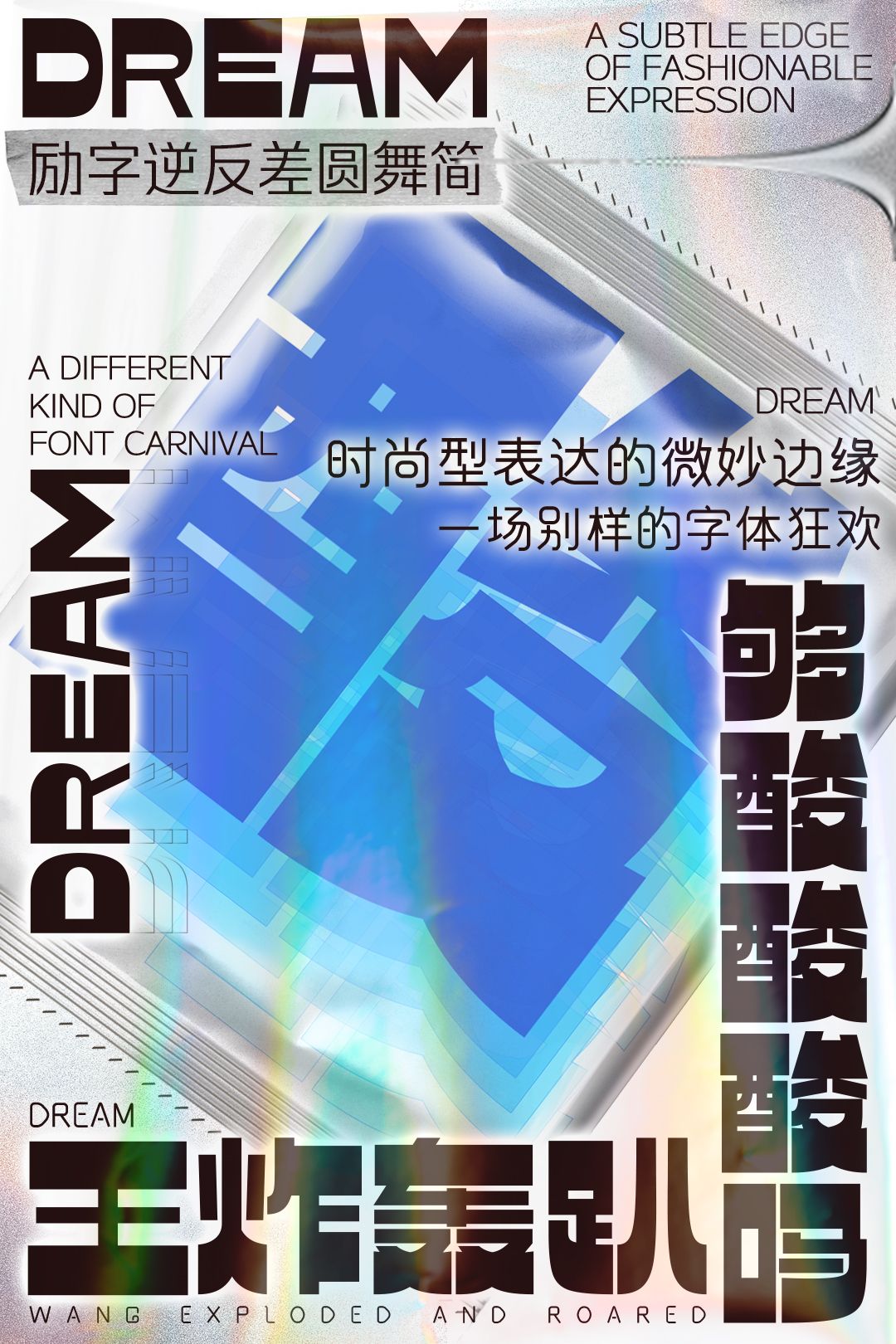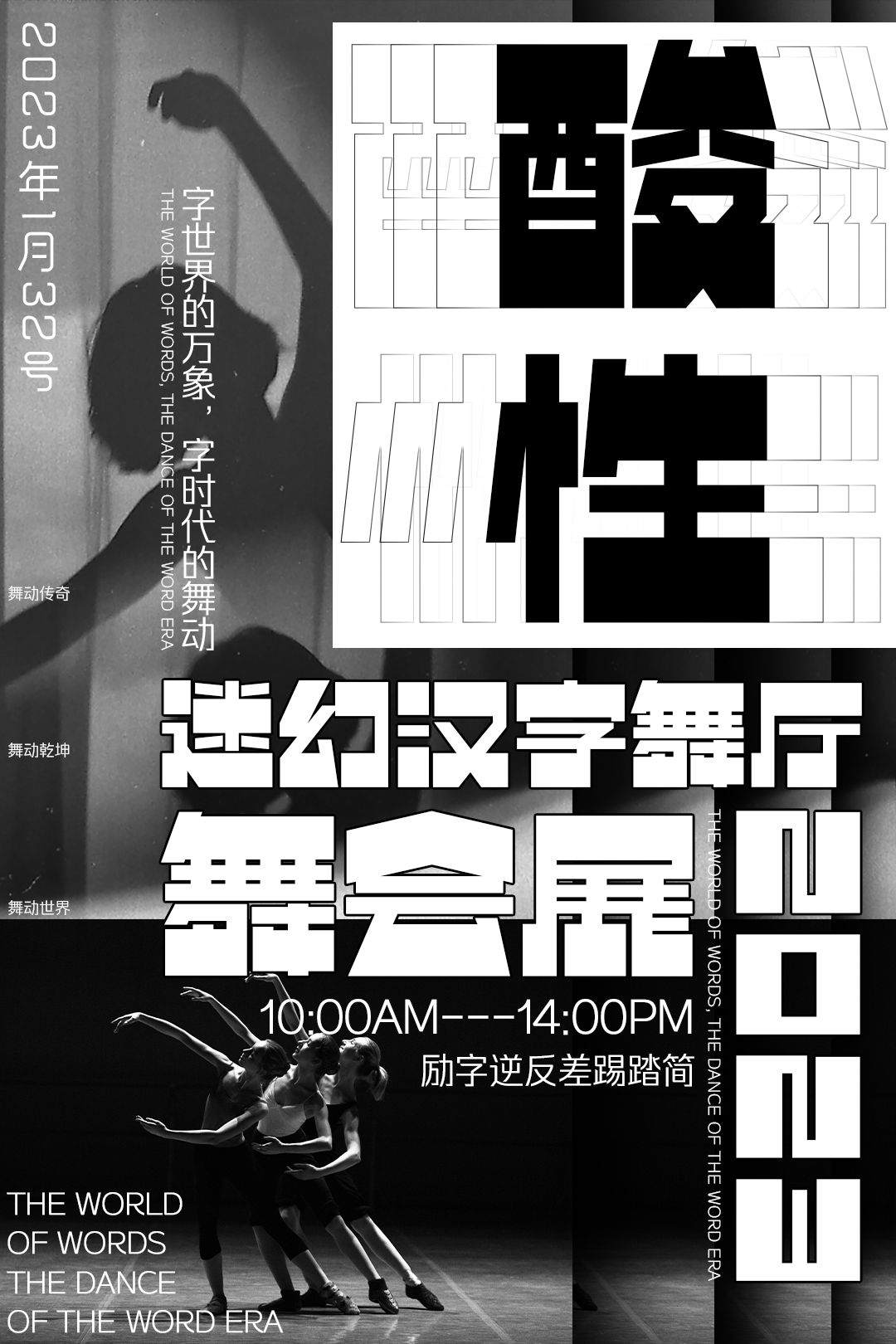
逆反差字体怎么火起来的?夸张、怪诞的字体美学风格用在哪?
逆反差字体的前身叫反对比字体(reverse contrast),至于为什么现在国内被大众称为逆反差字体? 也许是因为逆向差异感对字体设计有特别的记忆点。 逆反差字体,最初是由现代字体设计师Peter Biľak在 19 世纪早期发明的,当时创造该字体造型风格,目的就是为了吸引大众眼球,创造出更夸张、怪诞的字体美学风格。 逆反差字体很少用于正文,更多用于标题和海报等视觉化设计上,其中不寻常的结构特别引人注目和引发思考。
因为逆反差字体用作设计作品时吸引力十足,它夸张且极具张力的美学造型让人过目不忘。挑战着人类对新美学的全新认知,这种特殊的美学处理手法,让我们记忆犹新。励字战士推荐两款音乐主题的逆反差字体,一起来极致扭动吧~
励字逆反差圆舞简,是一款横平竖直、顶部底部笔画厚重、中间笔画极细的逆反差直线字体。起笔收笔采用平直的特点,中宫宽阔、重心平稳、布白均匀。笔画摒弃繁琐特点,转折处均以直角的处理方式。顶部底部笔画灰度极度夸张。点笔画根据空间有多种表达方式、灵活多变。笔画对称、镜像的处理方式使得结构更为工整。
励字逆反差踢踏简,字型方正、软硬兼备、笔画粗细对比明显的逆反差圆弧字体。在逆反差直线版基础上将撇笔画、捺笔画、钩笔画、部分点笔画运用弧线处理、弧度饱满。中宫较大,重心平稳。笔画对称。